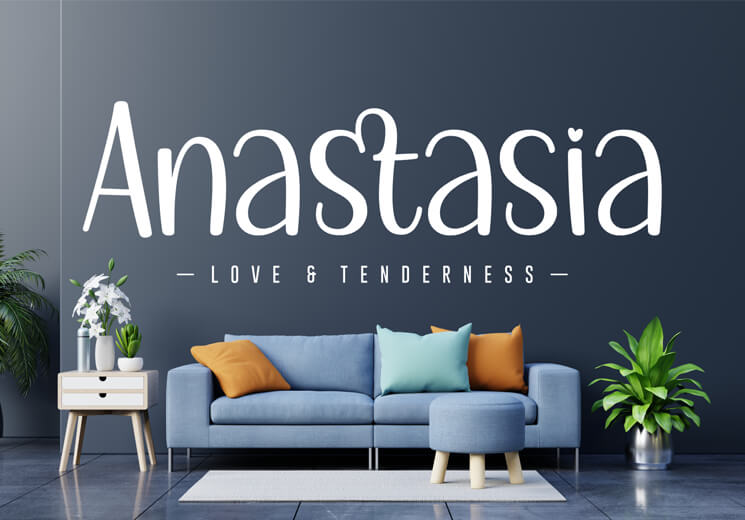
Anastasia
Eine verspielte Schriftart mit runden Formen und freundlichem Charakter. »Anastasia« steht kostenlos zum Download im Opentype-Format bereit.
Die Schrift verleiht Gestaltungen eine charmante, persönliche Note. Durch ihre weiche Linienführung lässt sie sich vielseitig einsetzen. Neben einigen Sonderzeichen und Ligaturen sind unter anderem auch deutschsprachige Umlaute enthalten.